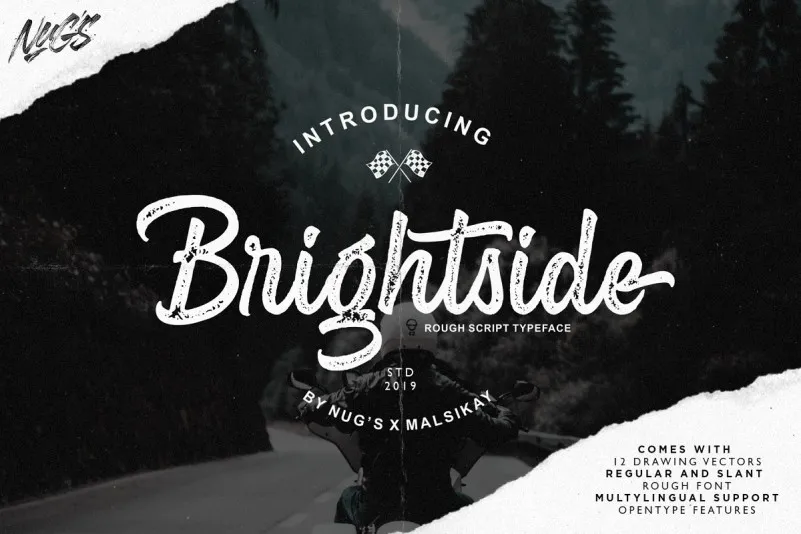
Brightside Script Font – Download Grátis
Agradecemos pela sua atenção! Estamos orgulhosamente apresentando uma nova fonte, a Brightside Script Font. Introduzimos esta vintage e elegante para qualquer tipo de design que necessite de um touch personalizado. A Brightside é uma fonte em estilo script com um toque vintage e textura rústica, tornando seus designs mais destacados. Estamos empolgados em apresentar a você a Brightside Script Font, uma escolha perfeita para qualquer projeto que exija um toque de sofisticação. Seja para adicionar um toque especial aos selos de produtos, personalizar logos ou criar material visuamente impactante, seja para o seu negócio, seus logotipos, catálogos, ou até mesmo para sua paixão pelo design e artes — a Brightside tem tudo o que você precisa. Seja você um designer amador ou profissional, a Brightside Script Font é uma escolha inteligente. Ela oferece a combinação perfeita de elegância vintage e personalização, tornando-a ideal para qualquer projeto em que deseje destacar sua marca de forma única e inovadora.